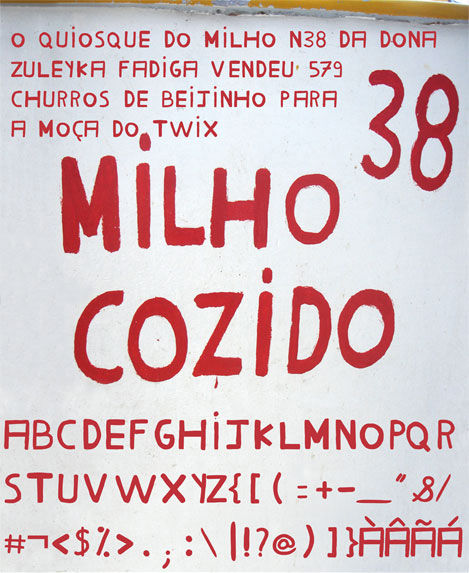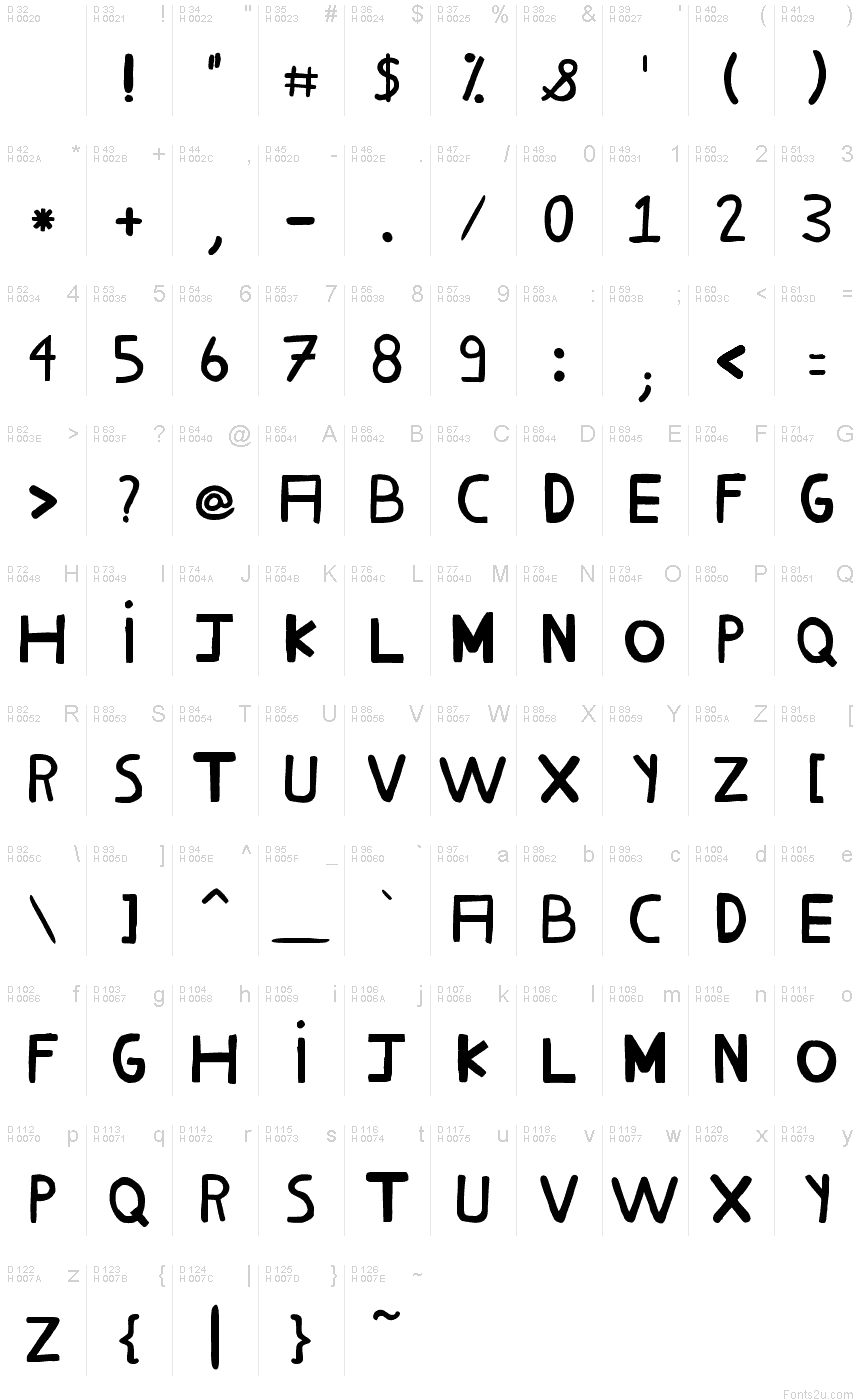
Milho Cozido je bezplatné titulkové písmo s erodovaným vzhledem od autorů Marcuse Dejeana a Andressy Ribeiro, které vyniká robustními, nepravidelnými velkými písmeny a výrazným ručně tvarovaným rytmem. Široké znaky působí, jako by byly vystřiženy z drsného papíru nebo namalovány hrubým štětcem; díky změkčeným okrajům a drobným nepravidelnostem působí tvary živě a nikoliv strnule.
Tento font zdarma patří na obaly potravin, plakáty na trhy, branding festivalů, obaly desek nebo hravé redakční sazby, kde trocha drsnosti podpoří koncept. Skvěle funguje také pro krátké nadpisy a titulky, protože těžké siluety přitahují pozornost, zatímco proměnlivá šířka a ručně opracované kontury zabraňují tomu, aby řádek působil příliš formálně.
Písmo založené na typografii používané u stánků s kukuřicí.
Milho Cozido — Prezentace písma